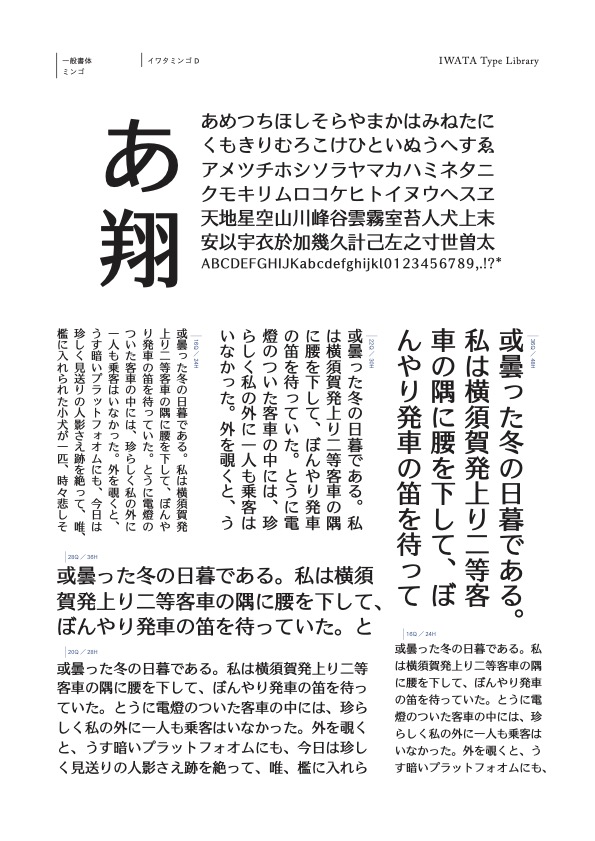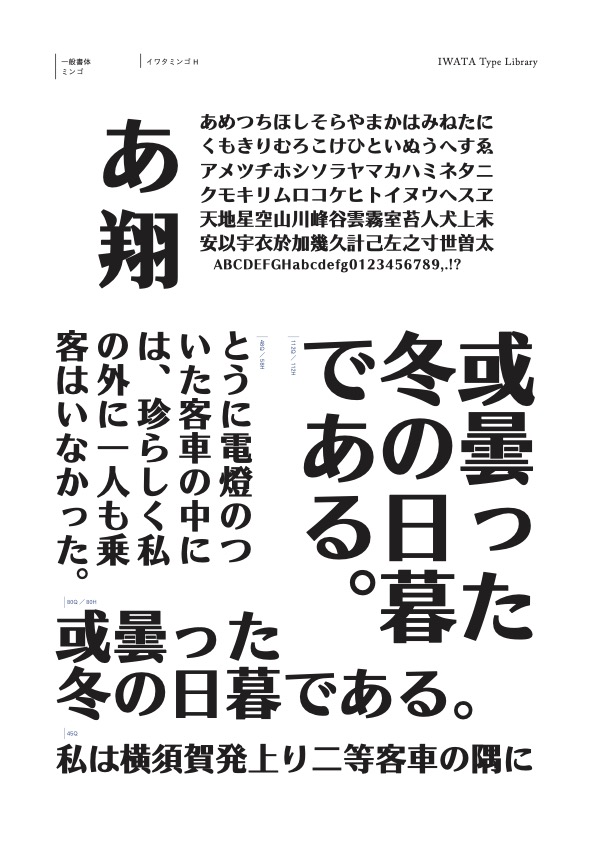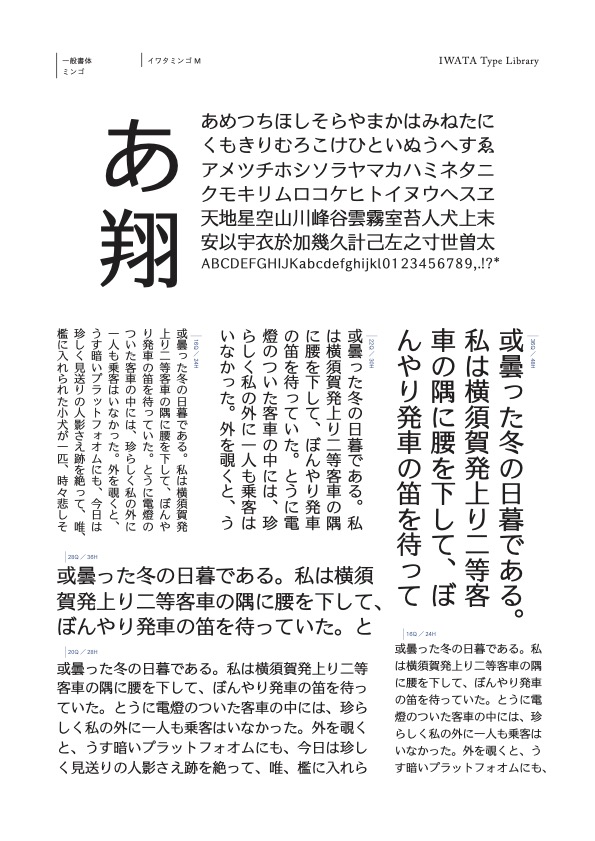
明朝体のシャープさ可読性の良さと、ゴシック体の力強さ整斉さを兼ね備えた、格調ある書体です。
文字のエレメントを単純化し、明るさとシャープさを表現し、文字の横線を太くして縦線との比率を少なくすることで、視認性を向上させました。
スッキリと見やすい独特なデザインは、印刷やディスプレイなど様々な媒体でご使用いただけます。